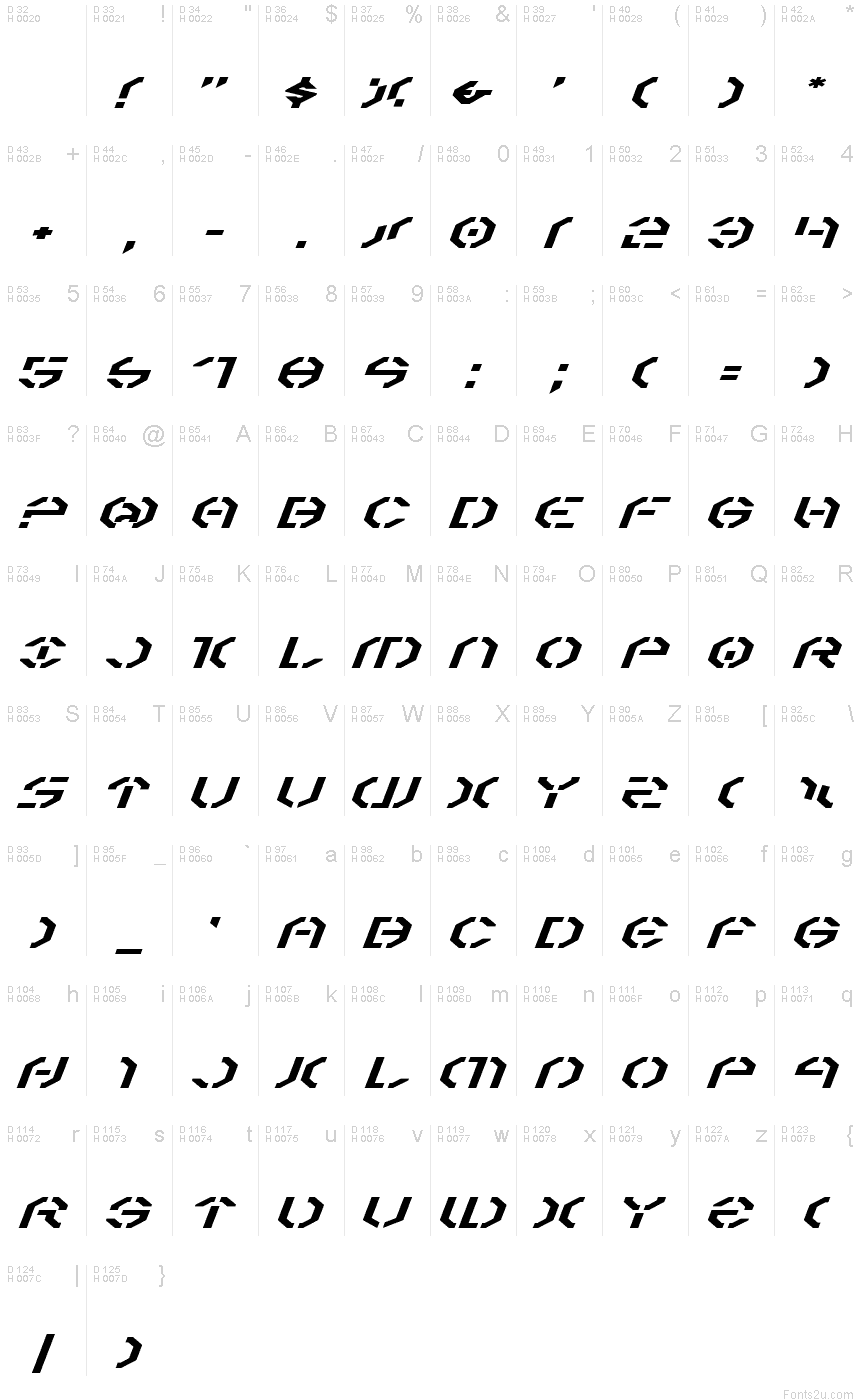
خط Year 3000 Expanded Italic من Iconian Fonts هو خط عرض (Display) مجاني مستقبلي يتميز بصورة ظلية حادة مائلة إلى الأمام. تبدو الحروف وكأنها منحوتة من ألواح زاوية، مع منحنيات ثمانية الأضلاع، وزوايا مقصوصة، وفتحات واسعة تمنح الخط إيقاعاً ميكانيكياً سريعاً دون أن يفقد طابعه الجرافيكي القوي.
وهو مناسب تماماً لملصقات الخيال العلمي، وشعارات الألعاب، والعلامات التجارية الخاصة بفعاليات التكنولوجيا، وعناوين الأغلفة، والبطاقات التعريفية حيث يمكن لهذه الحركة الحادة أن تؤدي الغرض. وبما أنه خط مجاني، فهو مناسب أيضاً لرسومات البث المباشر (Streamer graphics)، وأغلفة الألبومات، والعناوين القصيرة على التغليف، خاصة عندما تريد أن تبدو الحروف وكأنها جزء من آلة أو شعار سيارات سباق بدلاً من مجرد خط مائل عادي.